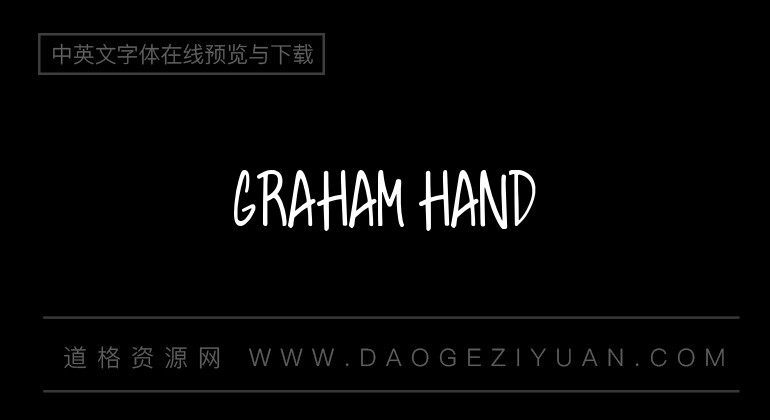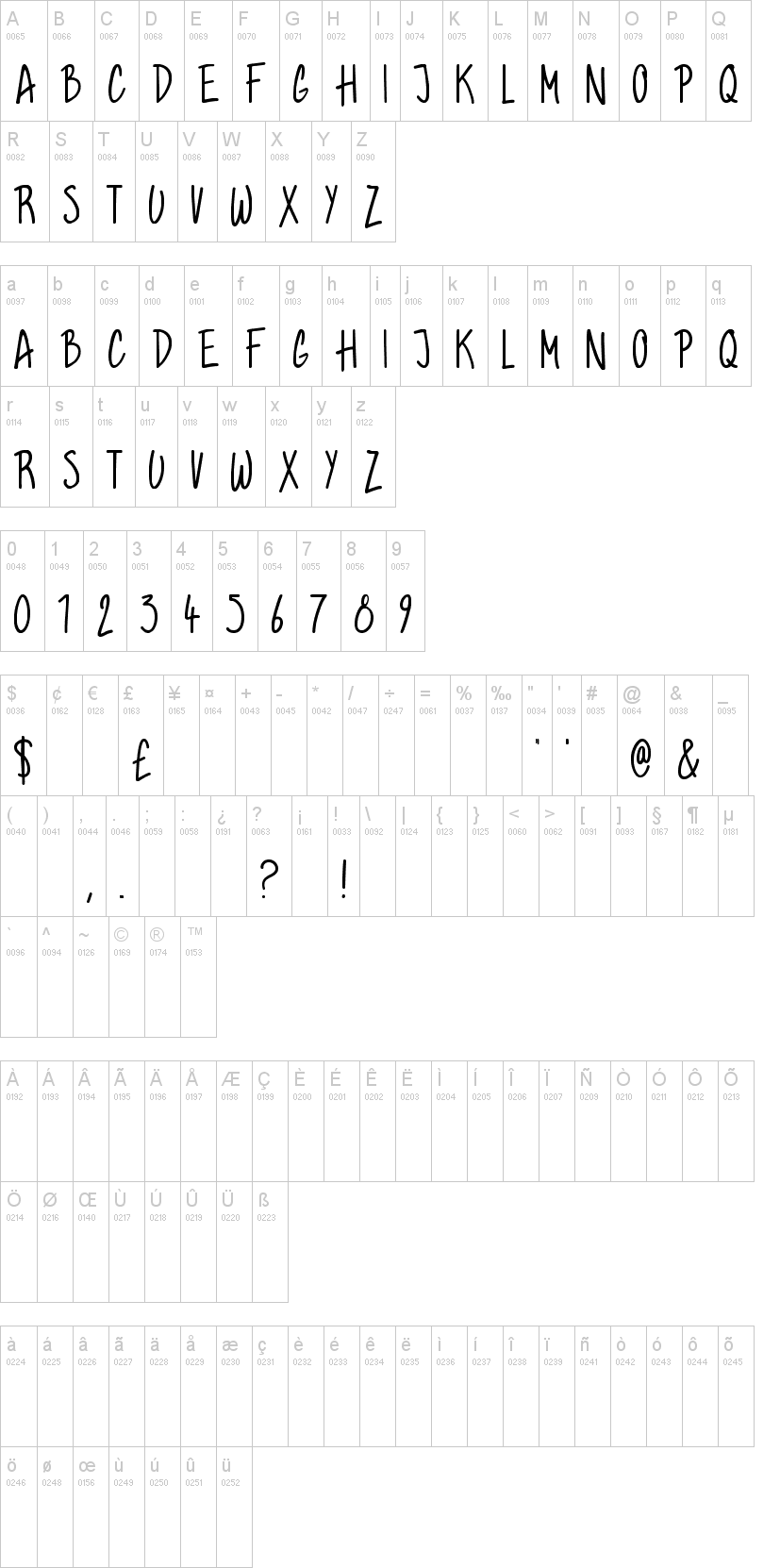
Graham Hand字体是由英国设计师Graham Meade专门为纸质出版物设计的一款字体,它具有非常优美的外观和节奏感,可以使文字变得更加精致而又不失传统的风格。Graham Hand字体的斜体字体也十分出色,使得文字更加有趣而又不失传统的风格。它可以用于出版物、网站、印刷品等等,可以让您的文字充满精致而又不失传统的风格。内容介绍
Graham Hand是一款非常不错的手写艺术字体,具有很好的视觉感,适合于文化类的宣传设计、商业类品牌的广告和产品包装设计以及个性化文字排版等较多场景。